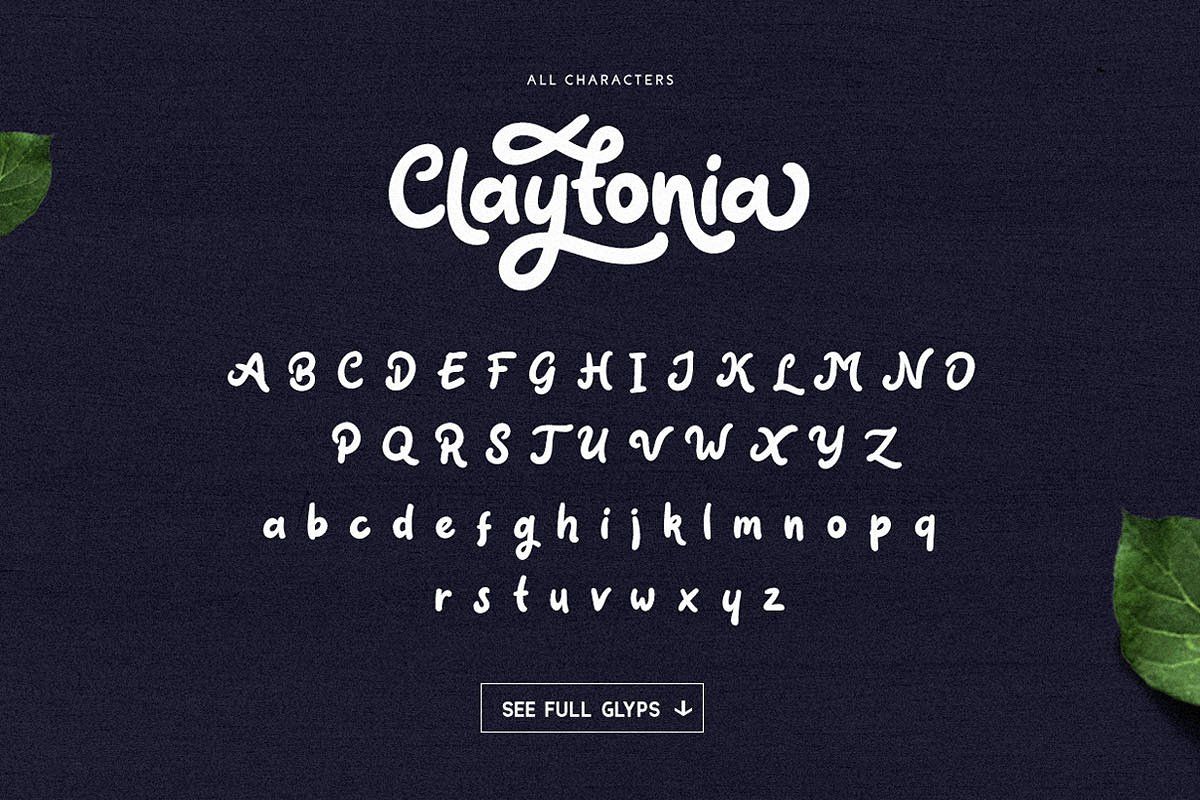
SVN-Claytonia là một bộ phông chữ thuộc dòng Script mang phong cách viết tay đầy tinh tế, gợi lên vẻ đẹp cổ điển pha lẫn nét hiện đại. Việc sử dụng font SVN-Claytonia Việt hóa cung cấp cho các kiến trúc sư và nhà thiết kế một công cụ tuyệt vời để tạo nên điểm nhấn cho các bản vẽ phối cảnh, bộ nhận diện thương hiệu homestay hay các ấn phẩm trang trí nội thất.
Đặc điểm thẩm mỹ nổi bật của dòng font SVN-Claytonia Việt hóa
Nét lôi cuốn đặc trưng của SVN-Claytonia nằm ở cấu trúc các ký tự uốn lượn nhịp nhàng, mô phỏng sinh động nét bút mực thủ công. Khác với các phông chữ hệ thống khô cứng, bộ phông này sở hữu nhịp điệu tự nhiên với độ thanh đậm biến thiên tinh tế, tạo nên chiều sâu thị giác lôi cuốn cho văn bản. Phiên bản font SVN-Claytonia Việt hóa đã được xử lý bảng mã Unicode chuẩn xác, giúp các dấu thanh phối hợp hài hòa với khung chữ chính, duy trì tính thẩm mỹ ổn định cho các nội dung trình bày tiếng Việt.
Sự ổn định của bộ phông này còn thể hiện ở khả năng truyền tải cảm xúc và định hình phong cách lãng mạn, sang trọng. Những đường nét được tinh chỉnh kỹ lưỡng giúp văn bản toát lên vẻ chỉn chu, phù hợp để làm điểm nhấn trên các bề mặt vật liệu như gỗ hoặc mica. Đây là lựa chọn phù hợp cho những dự án đề cao gu thẩm mỹ cá nhân, sự tận tâm và mong muốn tạo ra ấn tượng khác biệt cho sản phẩm thiết kế và kiến trúc chuyên nghiệp.
Gợi ý từ chuyên viên: SVN-Claytonia đạt hiệu quả thị giác cao khi bạn sử dụng cho các tiêu đề chính hoặc các trích dẫn ngắn. Để tổng thể bản thiết kế đạt được sự cân bằng, bạn nên phối hợp phông chữ này cùng một kiểu chữ không chân (Sans-serif) tối giản cho phần nội dung thuyết minh chi tiết, giúp thông tin trở nên minh bạch và dễ đọc hơn.
03 Ứng dụng phông chữ SVN-Claytonia vào thực tế kiến trúc
Nhờ diện mạo giàu tính nghệ thuật và cá tính riêng, bộ phông chữ này mang lại giá trị thực tế cao trong khâu trang trí và quảng bá các công trình hiện đại:
- Hệ thống nhận diện cho Homestay & Resort: Những nét chữ mềm mại của font SVN-Claytonia rất ăn ý khi xuất hiện trên biển hiệu bằng gỗ khắc laser hoặc mica vàng gương tại các khu nhà lắp ghép nghỉ dưỡng. Phông chữ này giúp không gian toát lên vẻ thư thái và đẳng cấp.
- Thiết kế bìa hồ sơ dự án nghệ thuật: Sử dụng SVN-Claytonia cho tiêu đề trang lời tựa hoặc lời nhắn gửi giúp thể hiện phong cách làm việc chuyên nghiệp, gần gũi của đơn vị kiến tạo đối với khách hàng và chủ đầu tư.
- Trang trí không gian nội thất nghệ thuật: Bạn có thể dùng font này để làm tranh quotes trang trí hoặc cắt chữ nổi đèn neon tại phòng khách, sảnh đón khách văn phòng container nhằm tạo điểm nhấn đầy lôi cuốn cho không gian sống và làm việc.
03 Lưu ý để bố cục phông chữ SVN-Claytonia đạt hiệu quả cao
Để khai thác hiệu quả vẻ đẹp của dòng font đặc thù này mà không làm rối mắt người xem, người thiết kế nên lưu tâm một số kinh nghiệm kỹ thuật sau:
- Hạn chế viết hoa toàn bộ ký tự: Đặc trưng của dòng phông Script là sự liên kết nhịp nhàng giữa các chữ cái viết thường. Việc viết hoa toàn bộ cụm từ sẽ làm mất đi nhịp điệu tự nhiên và khiến tiêu đề trở nên thô cứng, thiếu thẩm mỹ.
- Kiểm soát khoảng cách dòng: Do cấu trúc chữ thường có các nét móc vươn dài, bạn nên thiết lập khoảng cách dòng thoáng một chút để các ký tự không bị chồng lấn, giữ được sự minh bạch cho văn bản khi nhìn từ xa.
- Lựa chọn màu sắc phù hợp: Phông chữ nghệ thuật phát huy hiệu quả thị giác cao khi phối cùng các tông màu trầm hoặc màu kim loại trên nền trung tính, giúp tôn vinh tinh thần sang trọng và chuyên nghiệp của bộ chữ.